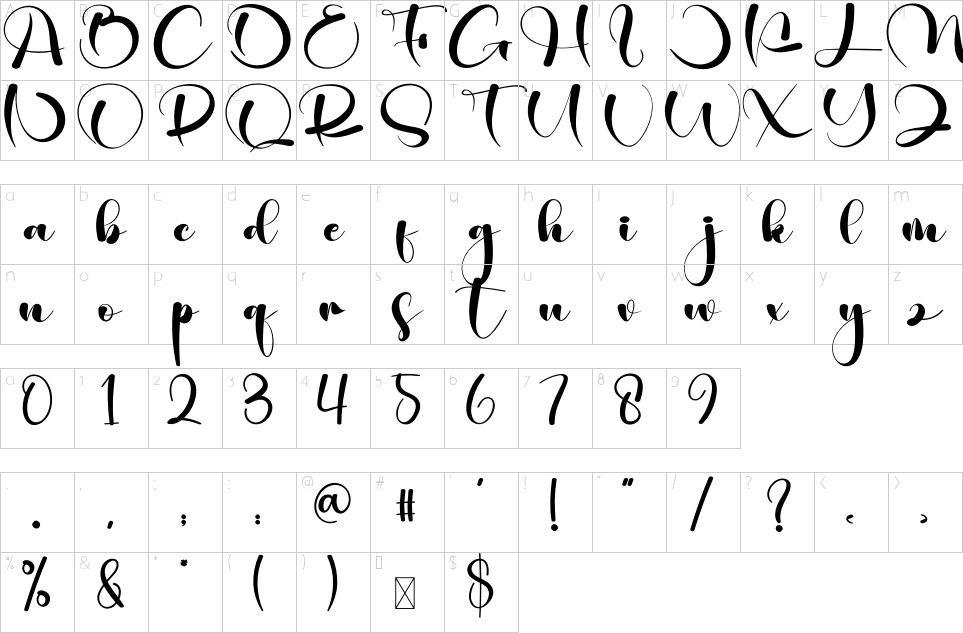
Autograph Font – Download Grátis
Descubra a autêntica essência da sua escrita com a Autograph font, uma escolha perfeita para criadores de conteúdo no Brasil. Desenvolvida por scratchones, esta fonte oferece um estilo elegante e sofisticado que combina perfeitamente com textos profissionais e editoriais. Com suporte para sistemas Windows e Mac, a Autograph é uma opção versátil para designers gráficos, profissionais de marketing digital, e qualquer pessoa que busque uma fonte de qualidade para seus projetos. Com seu design minimalista, esta fonte se adapta perfeitamente a diversas aplicações, seja para criar cartazes de eventos, design de sites, ou apenas para formatar seu texto em documentos pessoais. Sua liberdade de usar esta fonte gratuitamente para projetos pessoais e de negócios a torna um investimento valioso para qualquer criador de conteúdo.